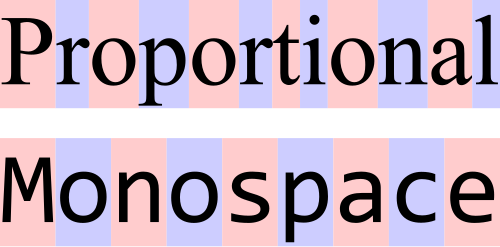
แบบอักษร
แบบอักษร (หรือตระกูลแบบอักษร ) คือการออกแบบตัวอักษรตัวเลขและสัญลักษณ์ อื่นๆ เพื่อใช้ในการพิมพ์หรือการแสดงผลทางอิเล็กทรอนิกส์[ 1 ]แบบอักษรส่วนใหญ่ประกอบด้วยรูปแบบต่างๆ เช่นขนาด (เช่น 24 พอยต์) น้ำหนัก (เช่น บาง หนา) ความลาดเอียง (เช่น ตัวเอียง) ความกว้าง (เช่น แคบ) และอื่นๆ แต่ละรูปแบบของแบบอักษรเหล่านี้เรียกว่าฟอนต์
มีแบบอักษรหลายพันแบบที่มีอยู่ และมีการพัฒนาแบบอักษรใหม่ๆ อย่างต่อเนื่อง
อาชีพออกแบบตัวอักษรเรียกว่าการออกแบบตัวอักษรผู้ที่ออกแบบตัวอักษรเรียกว่านักออกแบบตัวอักษรและมักทำงานในโรงหล่อตัวอักษรในงานจัดพิมพ์ด้วยคอมพิวเตอร์นักออกแบบตัวอักษรบางครั้งก็เรียกว่า "นักพัฒนาแบบอักษร" หรือ "นักออกแบบแบบอักษร" ส่วนผู้ที่ใช้ตัวอักษรในการออกแบบเค้าโครงหน้ากระดาษเรียกว่านักออกแบบตัวอักษร
แบบอักษรทุกแบบประกอบด้วยกลุ่มของสัญลักษณ์ซึ่งแต่ละสัญลักษณ์แทนกราฟีม–ตัวอักษร ตัวเลข เครื่องหมายวรรคตอน หรือสัญลักษณ์อื่นๆ[ก]นอกจากนี้ยังมีแบบอักษรที่ออกแบบมาสำหรับงานเฉพาะทาง เช่นการทำแผนที่โหราศาสตร์หรือคณิตศาสตร์
ศัพท์เฉพาะ
ในงานพิมพ์แบบ มืออาชีพ [ b ]คำว่าtypefaceไม่สามารถใช้แทนกันได้กับคำว่าfont [ c ] เพราะในอดีตคำว่า font ถูกนิยามว่าเป็นตัวอักษรชุดหนึ่งและตัวอักษรที่เกี่ยวข้องในขนาดเดียว ตัวอย่างเช่น Caslon Italic ขนาด 8 พอยต์เป็น font หนึ่ง และ Caslon Italic ขนาด 10 พอยต์เป็นอีก font หนึ่ง ในอดีต font มาจากโรงหล่อตัวอักษรในรูปแบบของชุด " sorts " โดยมีสำเนาของแต่ละตัวอักษรจำนวนหนึ่งรวมอยู่ด้วย
เมื่อรูปแบบตัวอักษรมีความหลากหลายมากขึ้นและความต้องการของสำนักพิมพ์ขยายวงกว้างขึ้นตลอดหลายศตวรรษที่ผ่านมา ตัวอักษรที่มีความหนา (ความเข้มหรือความอ่อน) และรูปแบบต่างๆ ที่ เฉพาะเจาะจง —โดยทั่วไปคือแบบปกติหรือแบบโรมันซึ่งแตกต่างจากแบบตัวเอียงรวมถึงแบบตัวแคบ—ได้นำไปสู่ การเกิด ตระกูลตัวอักษรซึ่งเป็นกลุ่มของตัวอักษรที่มีความสัมพันธ์กันอย่างใกล้ชิดและอาจมีหลายร้อยแบบ ตระกูลตัวอักษรโดยทั่วไปคือกลุ่มของตัวอักษรที่เกี่ยวข้องกันซึ่งแตกต่างกันเฉพาะในความหนา การวางแนวความกว้างฯลฯ แต่ไม่ใช่การออกแบบ ตัวอย่างเช่นTimesเป็นตระกูลตัวอักษร ในขณะที่ Times Roman, Times Italic และ Times Bold เป็นตัวอักษรแต่ละตัวที่ประกอบกันเป็นตระกูล Times ตระกูลตัวอักษรโดยทั่วไปประกอบด้วยตัวอักษรหลายตัว แม้ว่าบางตระกูล เช่นHelveticaอาจประกอบด้วยตัวอักษรหลายสิบตัวก็ตาม ในงานพิมพ์แบบดั้งเดิม ตระกูลฟอนต์หมายถึงชุดของฟอนต์ภายในแบบอักษรเดียวกัน เช่น ไทมส์โรมัน 8, ไทมส์โรมัน 10, ไทมส์โรมัน 12 เป็นต้น ส่วนในงานพิมพ์บนเว็บคำว่า "ตระกูลฟอนต์" ที่ระบุโดยใช้โค้ดHTMLspan style="font-family:อาจหมายถึง "ตระกูลแบบอักษร" หรือหมวดหมู่กว้างๆ เช่นแบบอักษรไม่มีเชิง (sans-serif)ซึ่งครอบคลุมตระกูลแบบอักษรหลายตระกูล
อีกวิธีหนึ่งในการมองความแตกต่างระหว่างฟอนต์คอมพิวเตอร์และแบบอักษรคือ ฟอนต์คอมพิวเตอร์เป็นภาชนะ—เช่น ซอฟต์แวร์—ที่ให้ชุดตัวอักษรที่มีลักษณะตามที่กำหนด ในขณะที่แบบอักษรคือการออกแบบตัวอักษรเหล่านั้นจริง ๆ[ 2 ]ดังนั้น แบบอักษรที่กำหนด เช่น Times อาจถูกแสดงผลด้วยฟอนต์ที่แตกต่างกัน เช่น ไฟล์ ฟอนต์คอมพิวเตอร์ที่สร้างโดยผู้ขายรายใดรายหนึ่ง ชุดตัวอักษรโลหะ เป็นต้น ใน ยุค ตัวอักษรโลหะฟอนต์ยังหมายถึงขนาดจุดที่เฉพาะเจาะจง แต่ด้วยฟอนต์โครงร่างแบบปรับขนาดได้แบบดิจิทัล ความแตกต่างนี้จึงไม่ถูกต้องอีกต่อไปเนื่องจากฟอนต์เดียวสามารถปรับขนาดได้ทุกขนาด
ตระกูลฟอนต์ "ขยาย" ชุดแรก ซึ่งรวมถึงความกว้างและน้ำหนักที่หลากหลายในรูปแบบทั่วไปเดียวกัน ปรากฏขึ้นในช่วงต้นทศวรรษ 1900 โดยเริ่มจากCheltenhamของATF (1902–1913) ซึ่งออกแบบครั้งแรกโดย Bertram Grosvenor Goodhue และมีแบบอักษรเพิ่มเติมอีกมากมายที่ออกแบบโดยMorris Fuller Benton [ 3 ] ตัวอย่างในภายหลัง ได้แก่Futura , Lucida , ITC Officinaบางตระกูลกลายเป็นซูเปอร์แฟมิลีอันเป็นผลมาจากการฟื้นฟู เช่นLinotype Syntax , Linotype Universในขณะที่บางตระกูลมีรูปแบบทางเลือกที่ออกแบบมาเพื่อใช้ทดแทนกันได้ เช่นCompatil , Generis
กลุ่ม แบบอักษรขนาดใหญ่ ( Superfamily)เริ่มปรากฏขึ้นเมื่อโรงหล่อเริ่มรวมแบบอักษรที่มีโครงสร้างแตกต่างกันอย่างมาก แต่มีความสัมพันธ์กันในด้านการออกแบบ ภายใต้ชื่อตระกูลเดียวกัน อาจกล่าวได้ว่ากลุ่มแบบอักษรขนาดใหญ่กลุ่มแรกเกิดขึ้นเมื่อ มอร์ริส ฟูลเลอร์ เบนตัน สร้าง Clearface Gothic ให้กับ ATF ในปี 1910 ซึ่งเป็นแบบอักษรไม่มีเชิง (sans-serif) ที่เป็นคู่กับ Clearface ที่มีอยู่เดิม (มีเชิง) จากมุมมองของนักออกแบบตัวอักษร คำว่า "กลุ่มแบบอักษรขนาดใหญ่" ไม่รวมถึงชุดแบบอักษรที่ไม่เกี่ยวข้องกันซึ่งวางจำหน่ายภายใต้ชื่อตระกูลเดียวกันหรือคล้ายกัน ตัวอย่างเช่น โรงหล่อที่วางจำหน่ายCaslon AntiqueและFutura Black and Display ตั้งชื่อแบบอักษรเหล่านี้โดยเชื่อมโยงกับตระกูล Caslon และ Futura แม้ว่าโครงสร้างของแบบอักษรเหล่านั้นจะไม่เกี่ยวข้องกับตระกูลเหล่านั้นก็ตาม ดังนั้น นักออกแบบตัวอักษรจึงไม่ถือว่าCaslon AntiqueและFutura Black/Display เป็นสมาชิกที่ถูกต้องของกลุ่มแบบอักษรขนาดใหญ่ Caslon หรือ Futura ใดๆ
อักขระ เพิ่มเติมหรืออักขระ เสริม ที่ออกแบบมาเพื่อให้เข้ากับแบบอักษรหลักนั้นมีการใช้งานมานานหลายศตวรรษแล้ว ในบางรูปแบบ อักขระเหล่านี้ถูกวางจำหน่ายเป็นแบบอักษรแยกต่างหาก ในช่วงต้นทศวรรษ 1990 กลุ่มแบบอักษร Adobe Systems ได้นำเสนอแนวคิดของ แบบอักษร ชุดผู้เชี่ยวชาญซึ่งมีชุดอักขระเพิ่มเติมที่เป็นมาตรฐาน รวมถึงตัวพิมพ์เล็กตัวเลขแบบเก่าและตัวอักษรพิเศษเศษส่วนและตัวเชื่อมตัวอักษร เพิ่มเติม ที่ไม่พบในแบบอักษรหลักสำหรับแบบอักษรนั้น แบบอักษรเสริมยังรวมถึงตัวอักษรทางเลือก เช่นswashes , dingbatsและชุดอักขระทางเลือก ซึ่งเสริมแบบอักษรปกติภายใต้ตระกูลเดียวกัน[ 4 ]อย่างไรก็ตาม ด้วยการแนะนำรูปแบบแบบอักษรเช่นOpenTypeอักขระเสริมเหล่านั้นจึงถูกรวมเข้ากับแบบอักษรหลัก โดยอาศัยความสามารถของซอฟต์แวร์เฉพาะในการเข้าถึงอักขระทางเลือก
เนื่องจากระบบปฏิบัติการของ Apple และ Microsoft รองรับชุดอักขระที่แตกต่างกันในฟอนต์ที่เกี่ยวข้องกับแพลตฟอร์ม โรงพิมพ์บางแห่งจึงใช้ฟอนต์เฉพาะทางในรูปแบบที่แตกต่างออกไป ฟอนต์เหล่านี้รวมถึงอักขระที่ไม่มีในคอมพิวเตอร์ Macintosh หรือ Windows เช่น เศษส่วน ตัวเชื่อม หรืออักขระที่มีเครื่องหมายเน้นเสียงบางตัว เป้าหมายคือการส่งมอบชุดอักขระทั้งหมดให้กับลูกค้าโดยไม่คำนึงถึงระบบปฏิบัติการที่ใช้
ขนาด
ขนาดของแบบอักษรและฟอนต์นั้นวัดตามธรรมเนียมเป็นหน่วยพอยต์ [ 5 ] หน่วยพอยต์ได้รับการกำหนดแตกต่างกันไปในแต่ละช่วงเวลา แต่ปัจจุบันที่นิยมใช้มากที่สุดคือหน่วยพอยต์สำหรับการพิมพ์บนเดสก์ท็อป ซึ่งมีค่าเท่ากับ 1/72 นิ้ว (0.0139 นิ้วหรือ 0.35 มม. ) เมื่อระบุขนาดตัวอักษรเป็นหน่วยพอยต์หรือคิว ความสูงของช่อง emซึ่งเป็นกล่องที่มองไม่เห็นซึ่งโดยทั่วไปจะมีขนาดใหญ่กว่าระยะห่างจากส่วนที่ยื่นขึ้น สูงสุดไปยัง ส่วนที่ยื่นลงต่ำสุด เล็กน้อย จะถูกปรับขนาดให้เท่ากับขนาดที่ระบุ[ 6 ]ตัวอย่างเช่น เมื่อตั้งค่าHelveticaเป็น 12 พอยต์ ช่อง em ที่กำหนดไว้ในฟอนต์ Helvetica จะถูกปรับขนาดเป็น 12 พอยต์ หรือ1/6 นิ้วหรือ 4.2 มม . อย่างไรก็ตาม ไม่มีองค์ประกอบใดของ Helvetica ขนาด 12 พอยต์ที่จำเป็นต้องมีขนาด 12 พอยต์พอดี
โดยทั่วไป การวัดขนาดตัวอักษรมักใช้หน่วยที่ไม่ใช่หน่วยพิมพ์ เช่น ฟุต นิ้ว เมตร เพื่อวัดความสูงของตัวอักษรพิมพ์ใหญ่ นอกจากนี้ ขนาดตัวอักษรยังนิยมวัดเป็นมิลลิเมตร (มม.) และคิว ( kyuซึ่งเท่ากับหนึ่งในสี่ของมิลลิเมตรในภาษาญี่ปุ่นที่เขียนเป็นอักษรโรมัน) และนิ้วด้วย